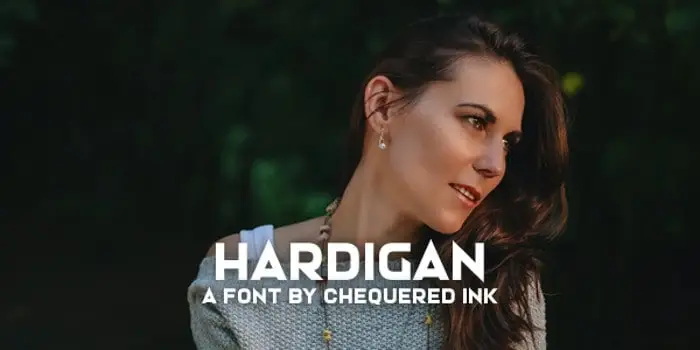
A Hardigan Sans Serif Font é uma seleção perfeita para projetos visuais criativos que valorizam a simplicidade e elegância na tipografia. Suas linhas retas e leves se destacam entre as demais, especialmente quando usadas em logotipos de marcas tecnológicas ou marcos digitais. Essa fonte exibida de maneira forte é perfeita para a criação de materiais publicitários como outdoors ou adesivos personalizados. Ela também se destaca na fabricação de embalagens, onde seu design minimalista pode complementar o aspecto funcional das mercadorias. A Hardigan Sans Serif é uma opção ideal tanto para designers digitais quanto para aqueles que desejam um design mais tradicional em suas criações. Além disso, a sua simplicidade também permite que seja usada em diversos tipos de mídia e produtos, desde camisetas até materiais de embalagem, tornando-a uma fonte versátil para qualquer projeto visual moderno.